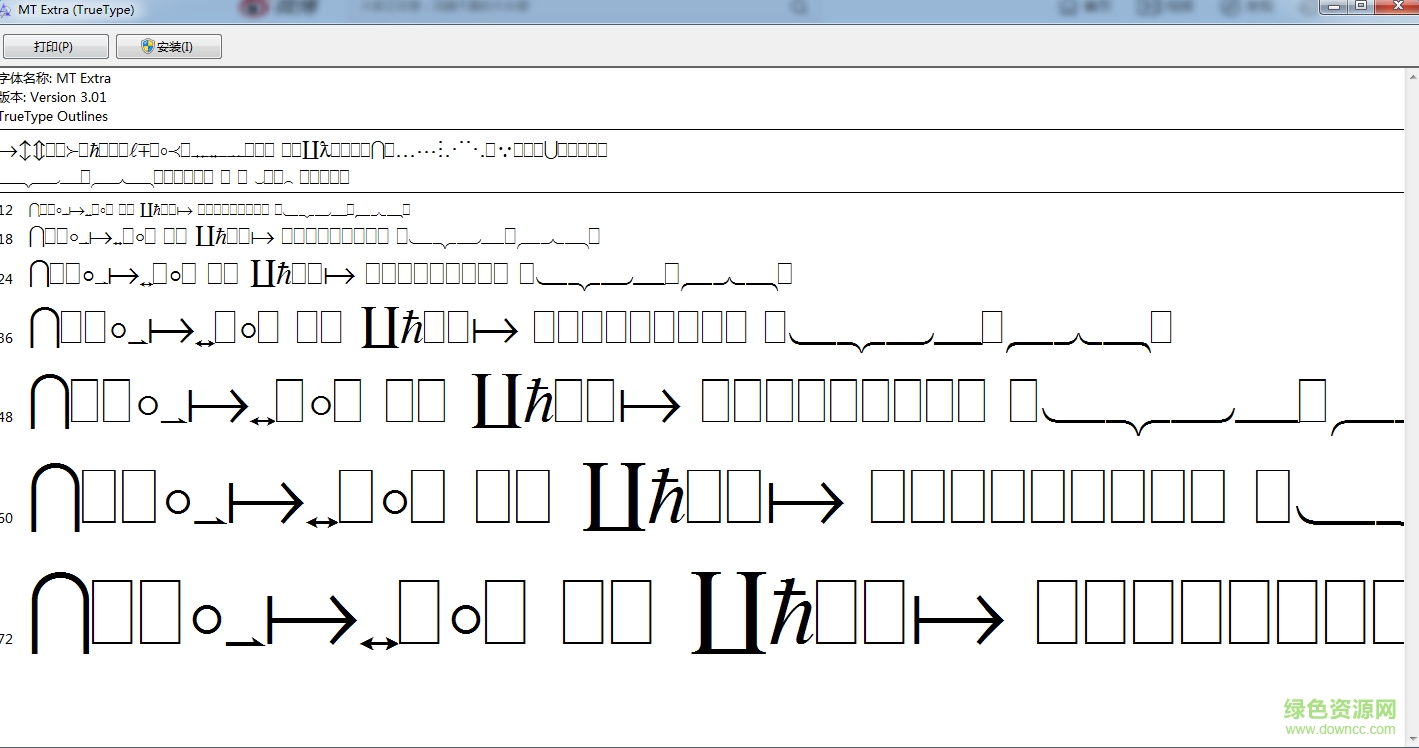
mt extra truetype 字體文件是一款ttf格式的符號字體包,包含了各種專業(yè)的數(shù)字符號,輸出效果良好,不過平常生活中不怎么用得到,有需要者快來綠色資源網(wǎng)下載吧!
MT Extra字體是一款用于符設(shè)計方面的字體,使用math type公式編輯器時經(jīng)常出現(xiàn)需要安裝這種字體的錯誤提示,原因是系統(tǒng)沒有安裝mtextra字體。